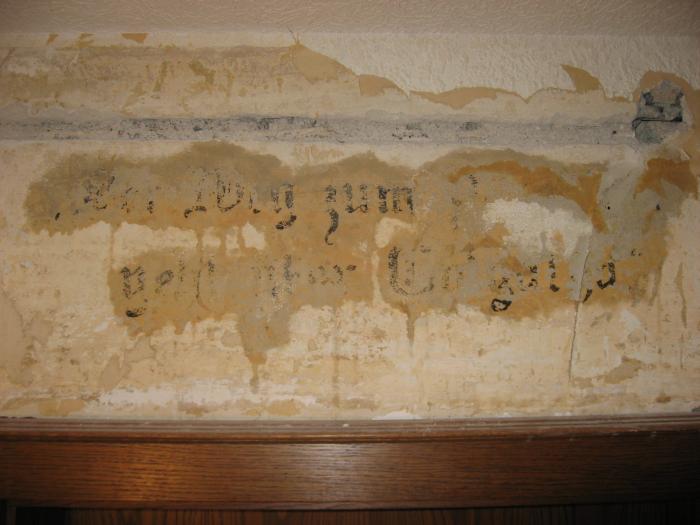
Wer kennt sich mit gotischen Schriften aus?
Wir haben beim renovieren über einer Tür eine Inschrift gefunden. Wir wüssten gern um welche Schrift es sich genau handelt, damit der Text wieder vervollständigt werden kann. "Der Weg zum Paradies geht über Gogatha!"
Die Schrift muss zwischen 1920 und 1930 angebracht worden sein.
Es ist mit Sicherheit eine gotische Schriftart, aber welche genau?
Das wurde mit Hand gemalt zu einer Zeit als die Bezeichnung ›Gotische Schrift‹ schon sehr genau war – der Rest ist Interpretation und Können des Malers. Da würde ich mir jetzt auch keinen ähnlichen Font für suchen, sondern jemanden, der sich damit auskennt und das nicht nur nachmalen sondern nachschreiben kann.
Nur falls es kein Tippfehler ist: Es fehlt auf jeden Fall ein "l". Und da verschiedene Schreibweisen möglich sind: Wenn ein "h" auftaucht, könnte auch ein "a" gefordert sein – zumindest die Lutherbibel und die Elberfelder Bibel haben "Golgatha" ... Ich kann den Buchstaben auf dem Bild nicht eindeutig erkennen.
Es ist auf jeden Fall ein passender Freiraum zwischen o und g, der auch Reste von einem passenden Buchstaben (oder Dreck) erkennen lässt.
Gutes Vergleichsmaterial um zumindest eine Schrift eines ähnlichen Stils zu finden, ist das mittlerweile recht umfangreiche Schriftenverzeichnis meines Fraktur-Digitalisier Kollegen Gerhard Helzel. http://www.romana-hamburg.de/Fraktur.htm Dort mal den Katalog mit jetzt 343 Schriftarten herunterladen. Es sollte doch mit dem Teufel zugehen, wäre da nicht zumindest entfernt ähnliches dabei.